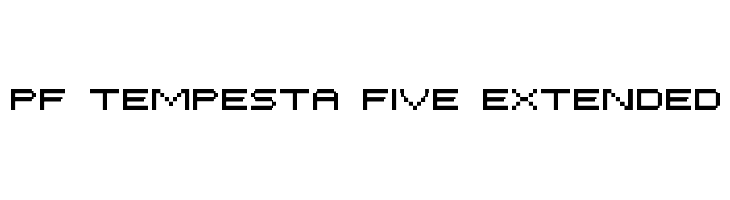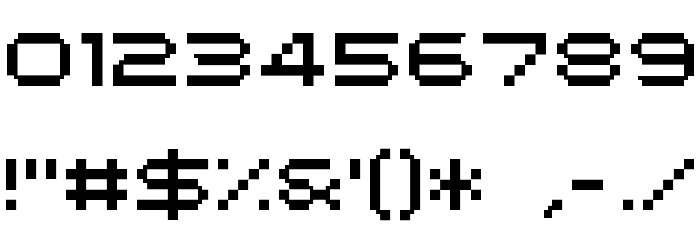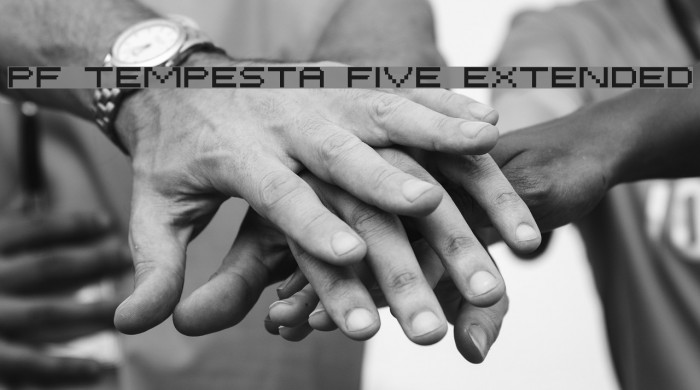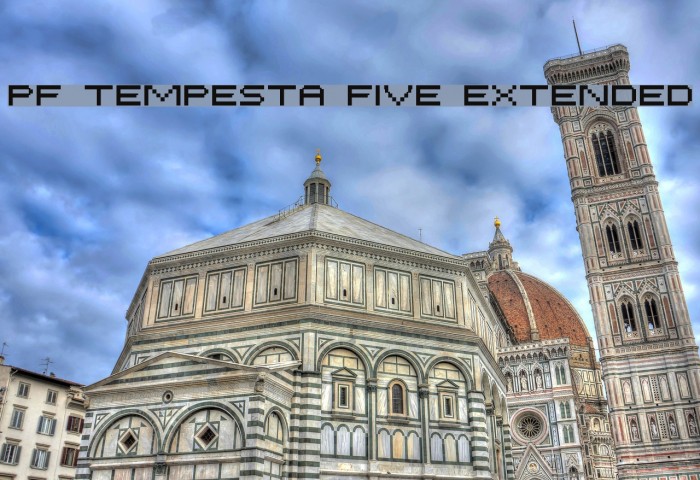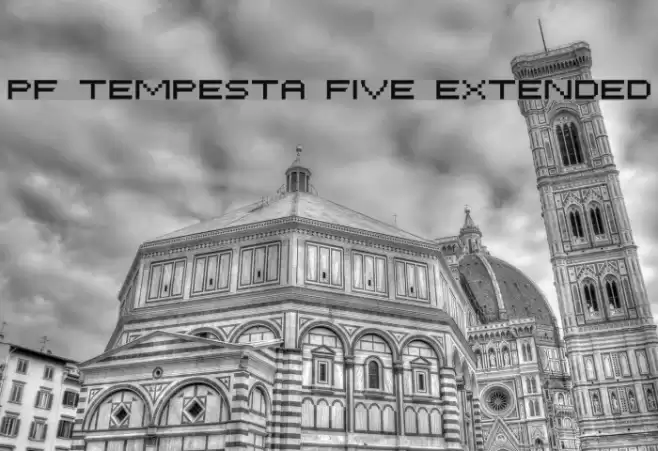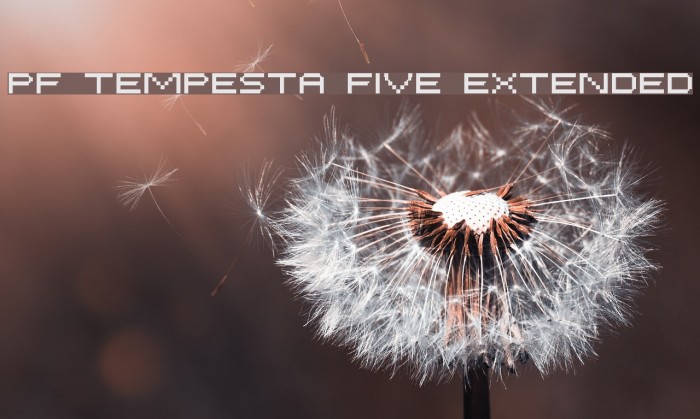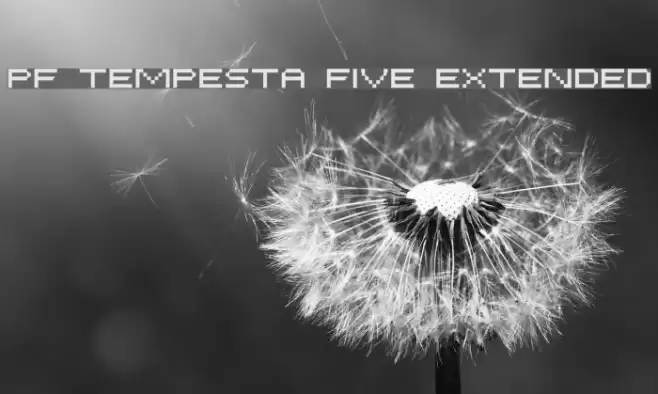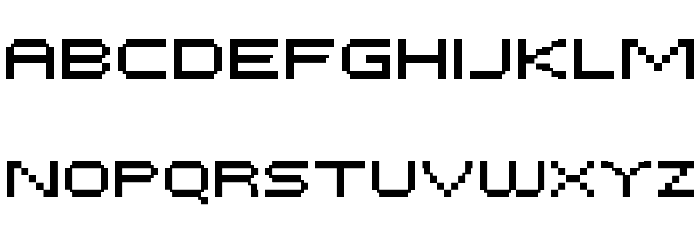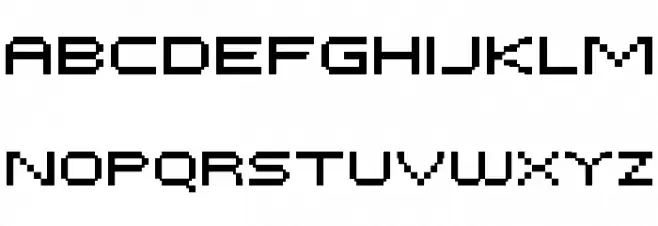
PF Tempesta Five Extended Font
| Estilo general | Vintage |
| Caso de uso | Headlines, Logos, Digital Art |
| Proyectos propuestos | Ideal for projects that aim to evoke nostalgia, such as retro video games, tech-themed posters, or digital art installations. |